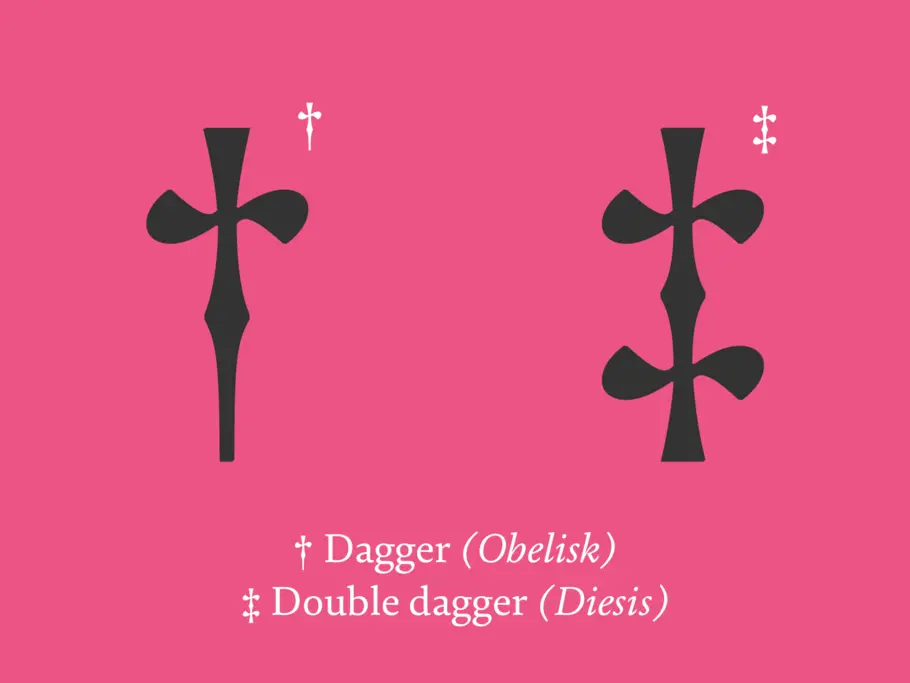
Série Ponctuation : L'obèle et le double obèle.
L'obèle est un symbole peu courant, dont peu connaissent l'existence. Mais lorsque j'ai conçu la police FS Brabo, c'était l'un de mes préférés. Il existe sous la forme d'un obèle et d'un double obèle, aussi appelé obel ou obélisque. Ces caractères de ponctuation peu connus ont pourtant de nombreux usages.
Le plus fréquent, pour les deux, est celui qui consiste à les utiliser dans les notes de bas de page après l’astérisque (*), plus courant.
*Première note de bas de page
†Deuxième note de bas de page
‡Troisième note de bas de page
L’obèle est également utilisé de façon moins joyeuse, pour indiquer un décès, lorsqu’il est placé immédiatement avant ou après le nom d’une personne : †Roi Henry VIII. Et lorsqu’il est placé à côté d’une date, cela symbolise l’année du décès (l’astérisque peut être utilisé de la même manière pour l’année de naissance) : †1547
Selon l›Oxford English Dictionary, l’obèle est également utilisé avec la mention Obs. pour indiquer qu’un terme est obsolète.
Mais ce n’est pas tout. Cette page Wikipédia décrit plusieurs autres usages, notamment les échecs, où l’obèle peut être utilisé pour indiquer qu’un coup a permis de mettre l’adversaire en échec, et le double obèle échec et mat. Au cricket, il désigne le gardien de guichet et en physique, un opérateur adjoint.
Alors, comment peut-on les insérer dans du texte ?